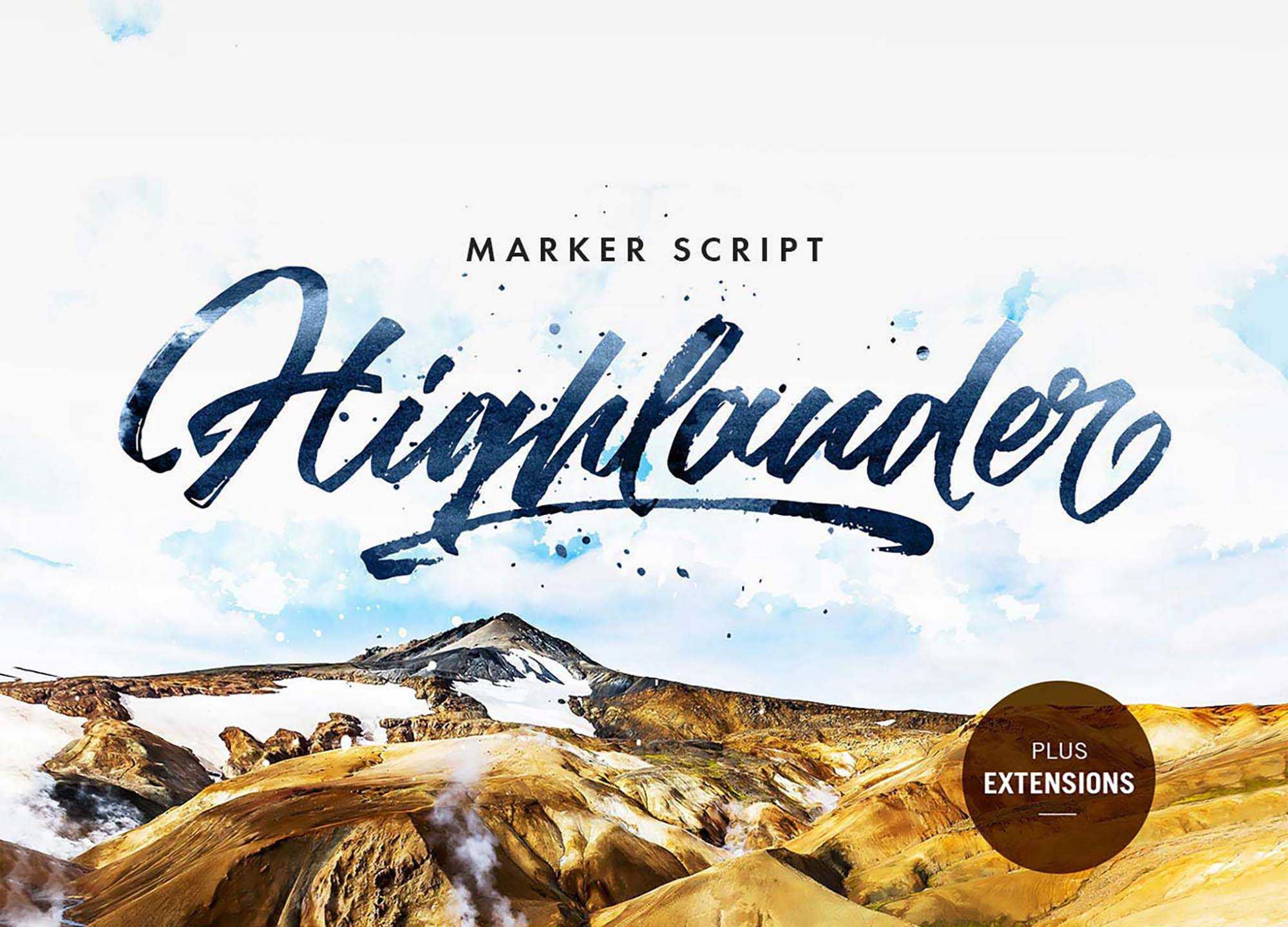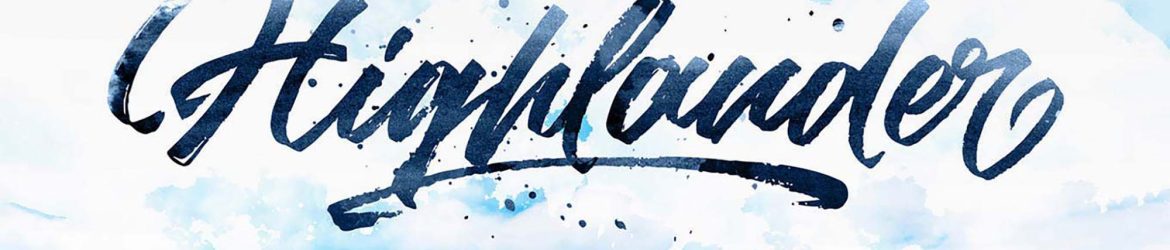
Highlander Marker Script Font – Download Grátis
Highlander Marker Script Font é uma fonte de script feita especialmente para aqueles que valorizam um estilo elegante e sofisticado. Inspirada no estilo de autoria livre, a Highlander traz uma elegância única com uma seleção de letras maiúsculas e minúsculas, números e sinais de pontuação. Esta fonte é perfeita para criar uma identidade visual forte e distintiva em design gráfico. Seja para criações de novela, canções, jogos de teatro ou simples desenhos, Highlander captura a essência da arte que vem de uma fonte, oferecendo uma escolha sofisticada e única. Esta fonte é perfeita para quem busca uma maneira distintiva de adicionar um toque especial a seus projetos.